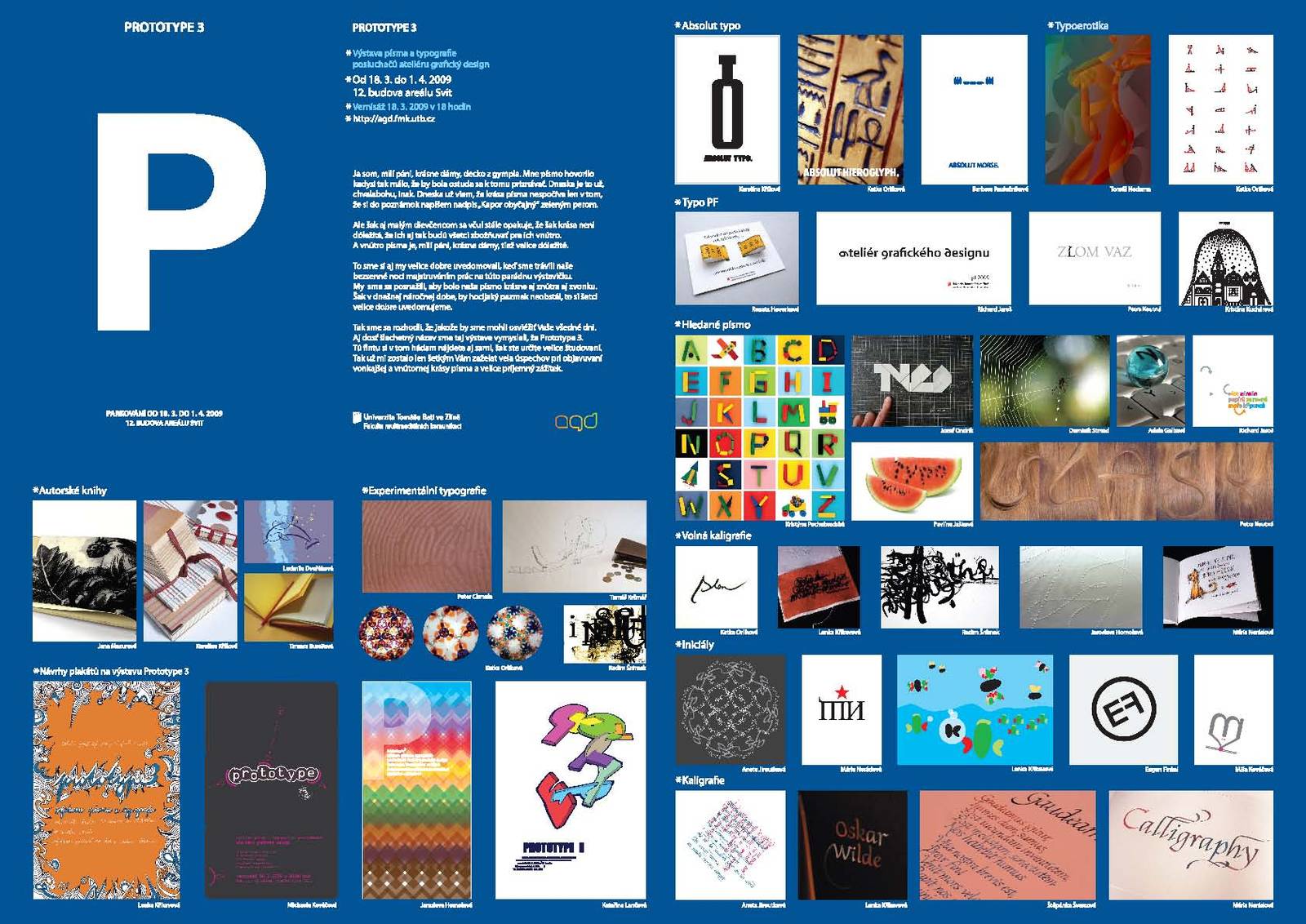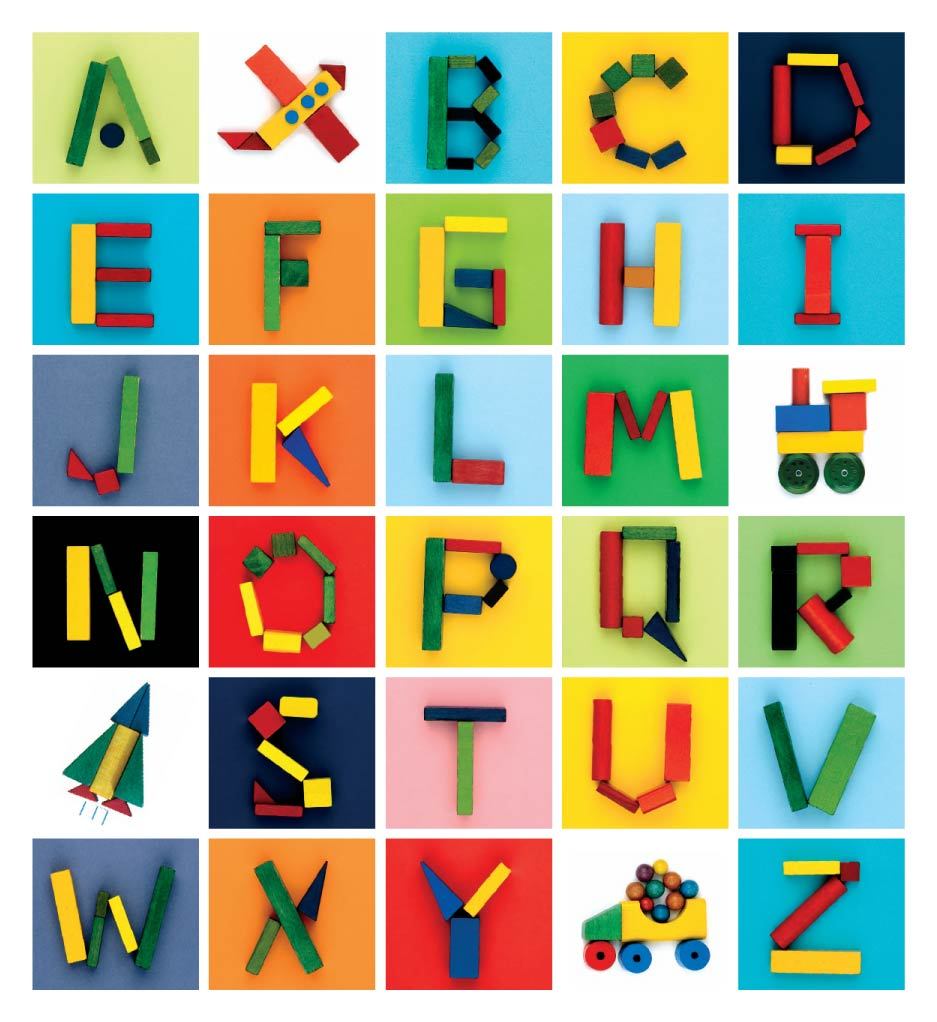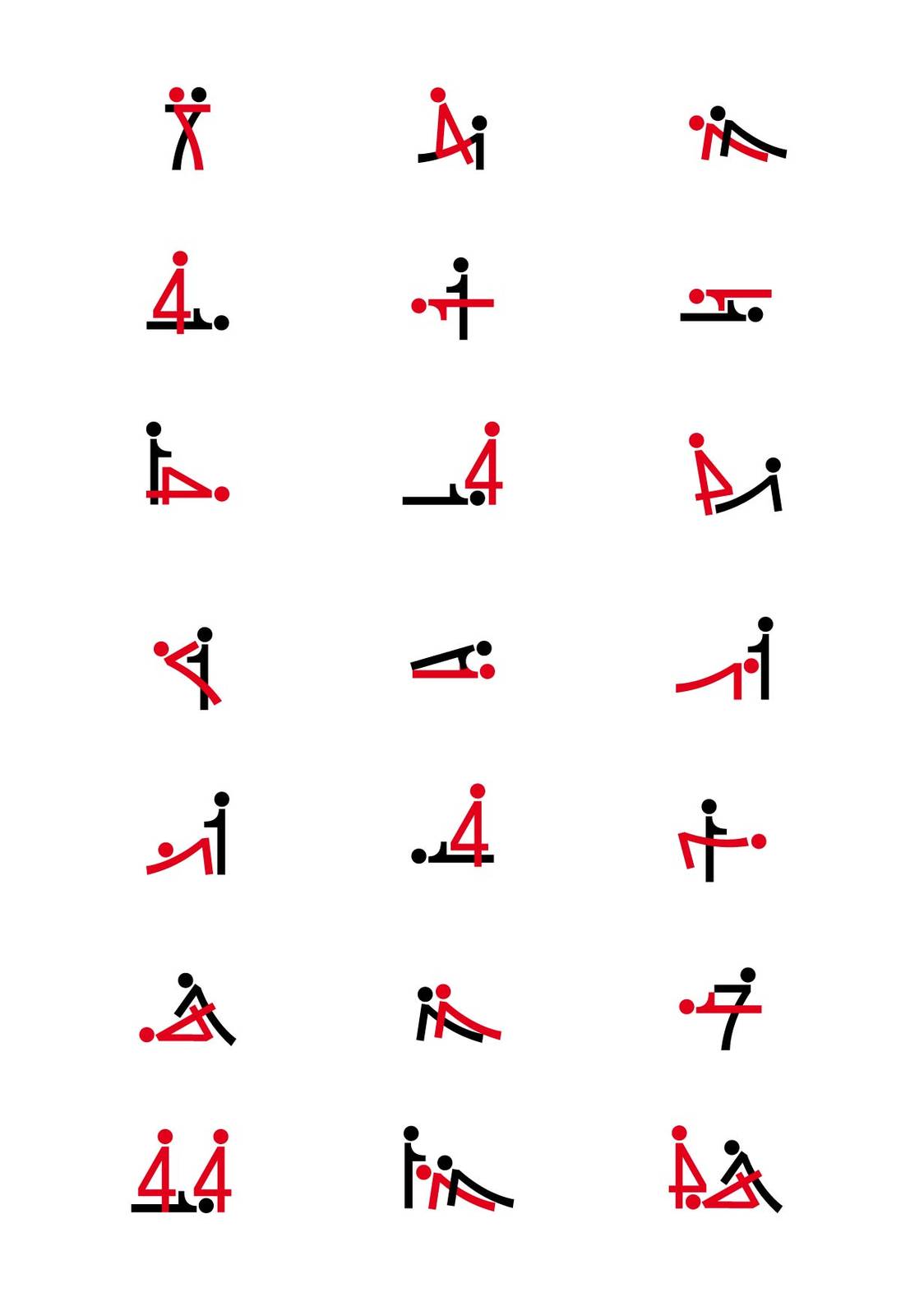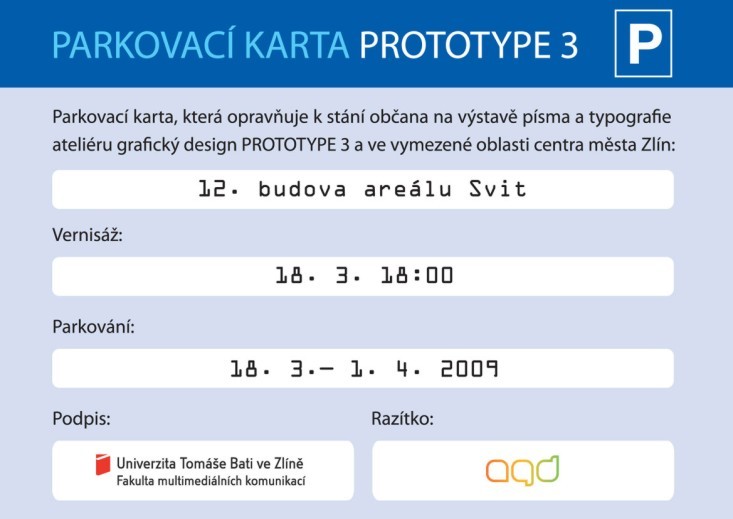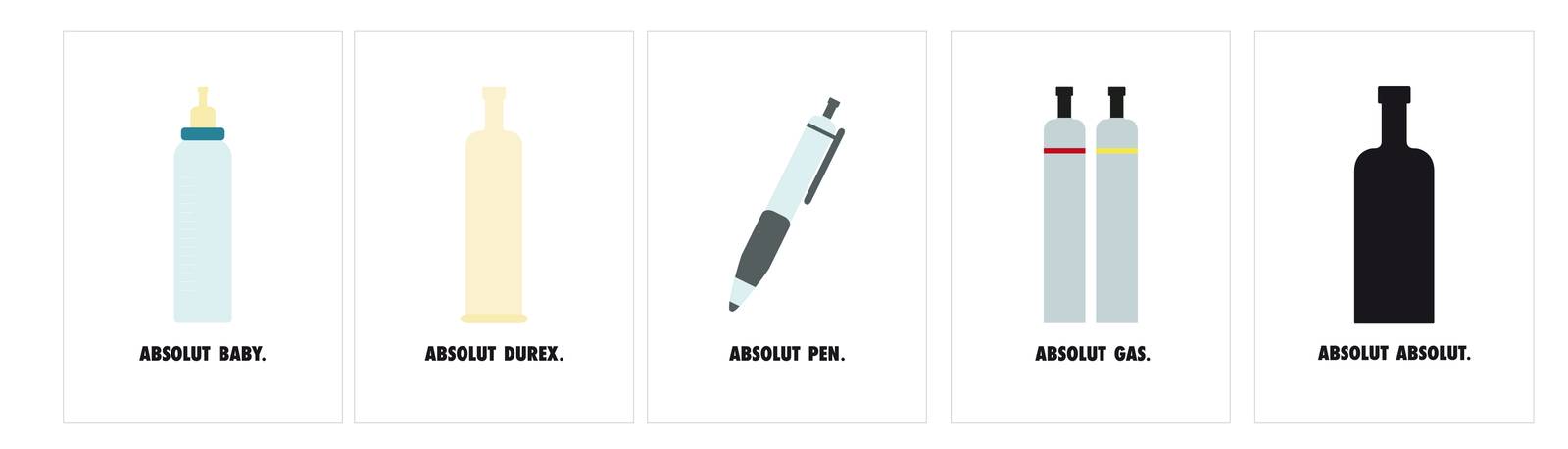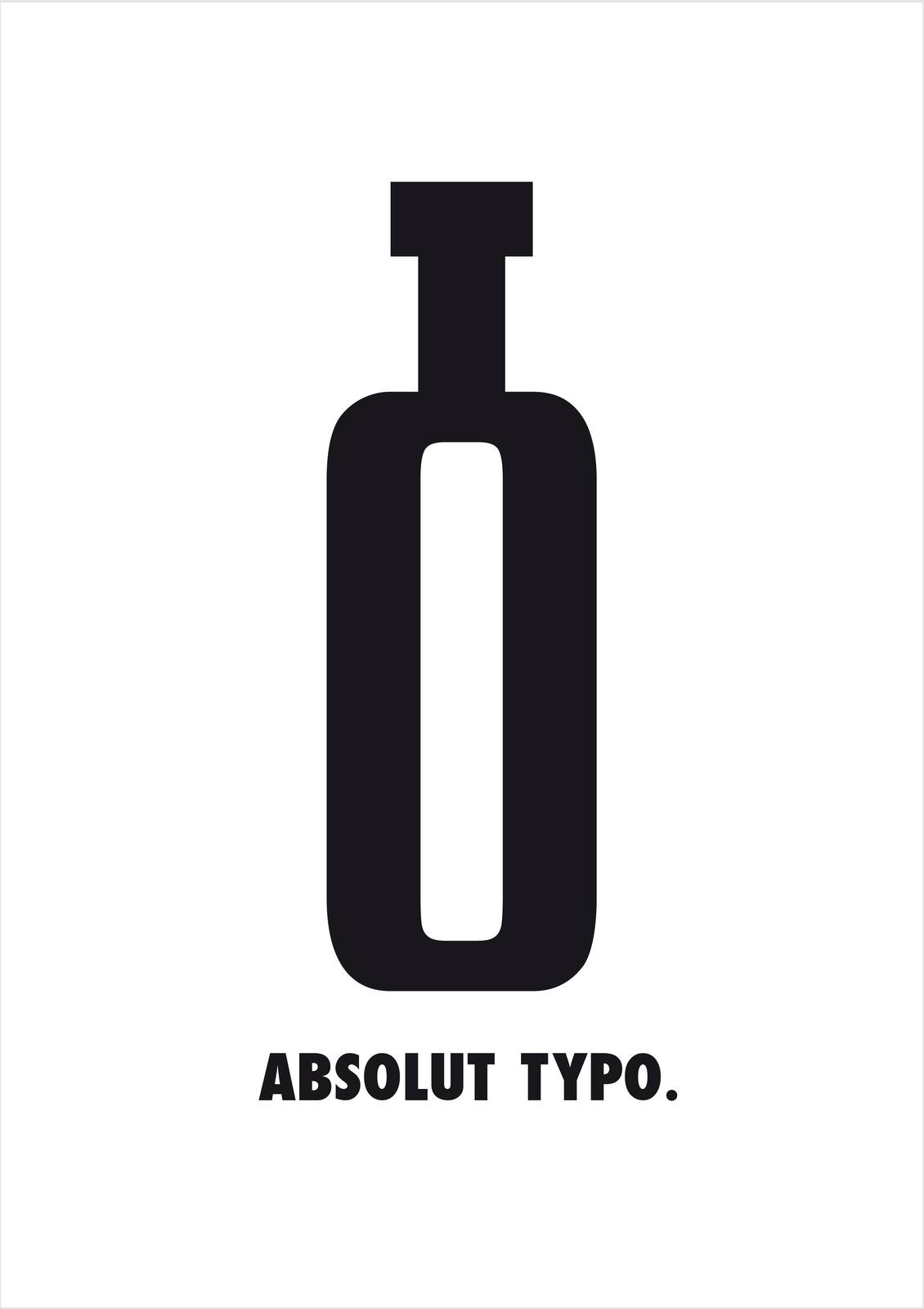
Prototype 3 – výstava písma a typografie ve Zlíně
Od 18. 3. probíhá v 12. budově bývalého areálu továrny Svit ve Zlíně rozsáhlá výstava písma a typografie studentů ateliéru grafický design Fakulty multimediálních komunikací Univerzity Tomáše Bati.
Projekt vznikl v rámci seminářů písma a typografie a zahrnuje práce studentů čtyř ročníků v posledních třech semestrech. Exponáty představují typografické řemeslo jako takové i kreativní projekty s použitím písma jako dekorativního artefaktu. Do 1. 4. 2009 je možno denně od 10 do 17 hod. shlédnout témata jako typoexperiment, absolut, typo, typoeros, typoanimace, typoinstalace, kaligrafie či autorské knihy.
ta se souložícími čísly bych přál snad každé škole v EU!